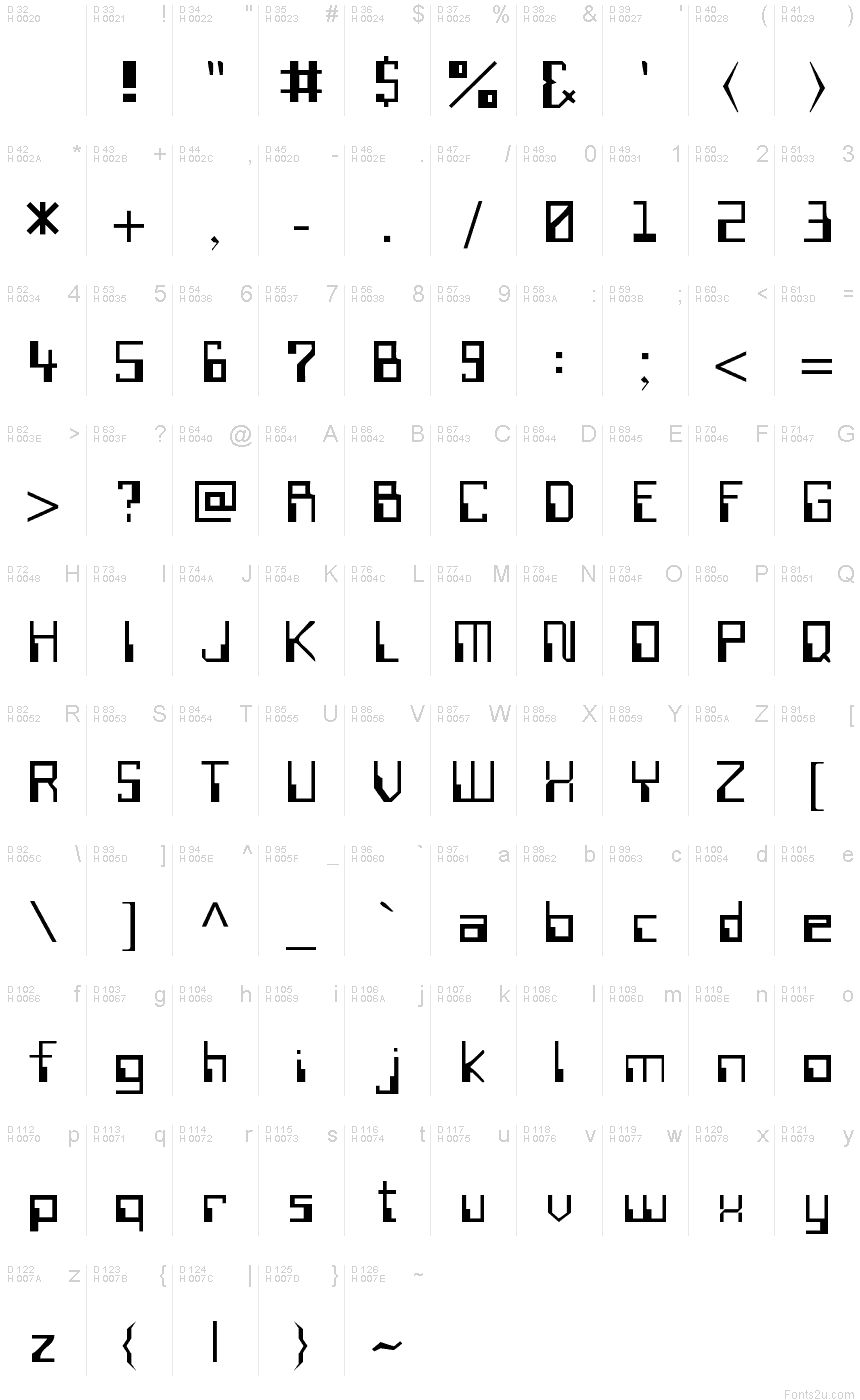
Sillycon Valley di Jim Ratliff è un font display pixel-techno gratuito con un carattere sbarazzino che ricorda i primi anni del digitale. Le lettere sono costruite con blocchi quadrati massicci e angoli retti decisi, conferendo all'alfabeto il fascino dei vecchi grafismi a schermo, dei menù di gioco e dei loghi fai-da-te dell'era informatica, piuttosto che un look futuristico e cromato.
Si adatta perfettamente al branding di software retro, poster arcade, copertine di fanzine, titoli e brevi headline su packaging, dove un font gratuito con bordi bitmap evidenti è una scelta consapevole. Usalo per testi brevi come testate, monogrammi e grandi titoli, perché il ritmo serrato dei blocchi e gli angoli a gradini attirano subito lo sguardo.